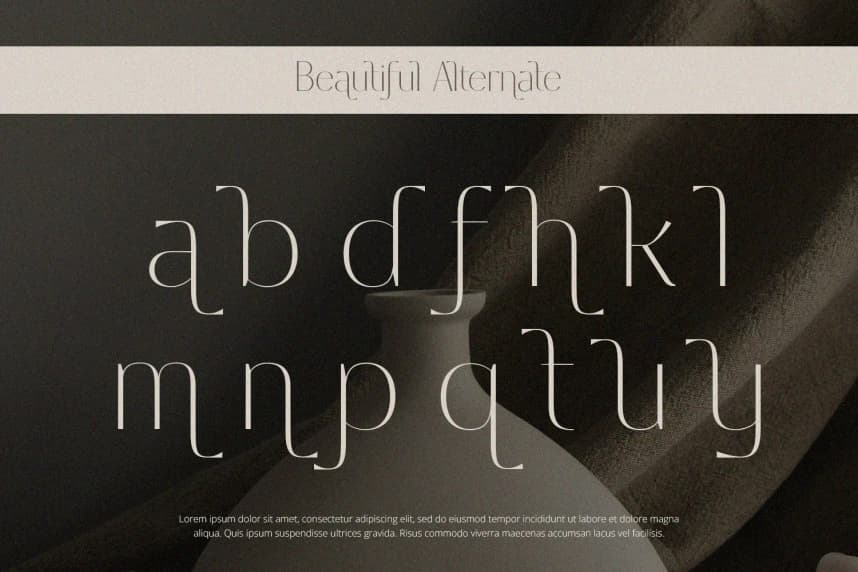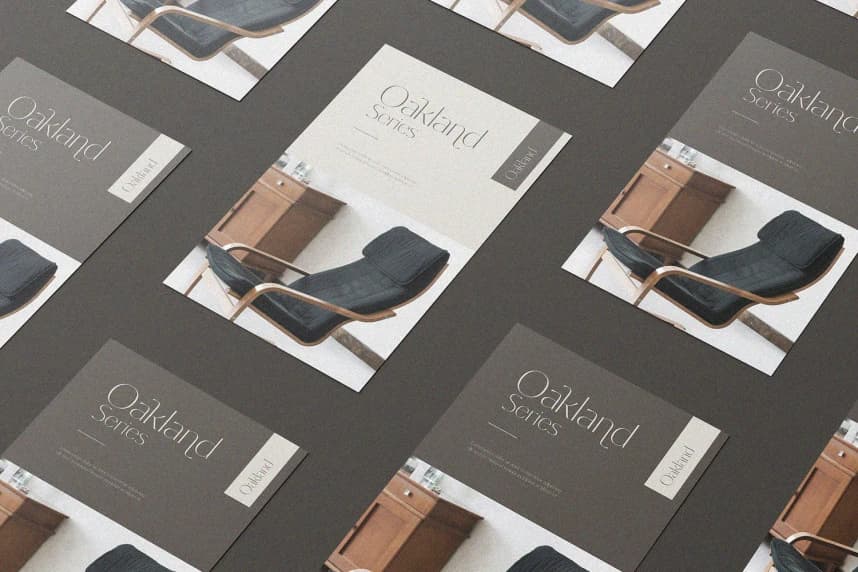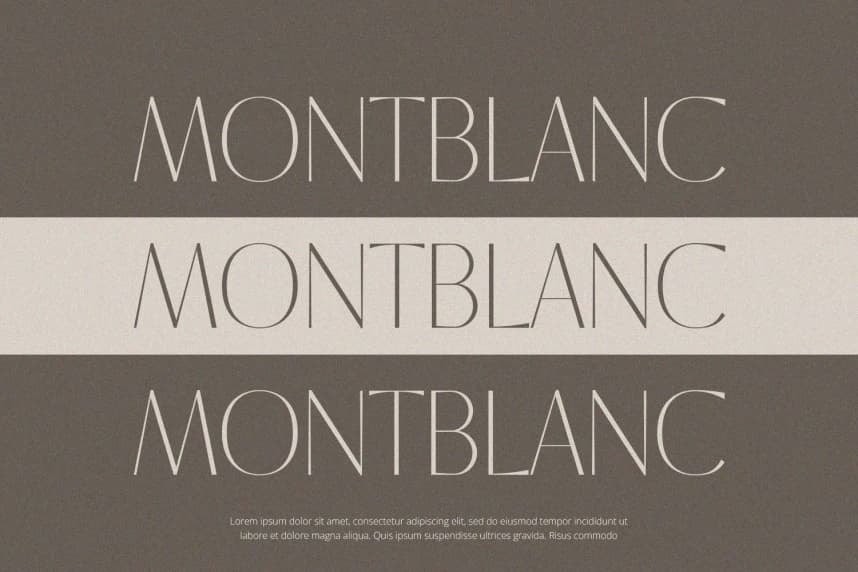
Castelloria - Serif Font, modern bir hissiyat veren bir serif yazı tipidir. Branding, Logo Design, Lettering, Logotype, Clothing, Poster, magazine, packaging, posters, shopping bags, t-shirts, book covers, photography, special events ve diğer design projeleri için mükemmel şekilde kullanılacaktır.
Castelloria - Serif Font, modern hissiyat veren bir serif yazı tipidir. Markalaştırma (Branding), Logo Tasarımı, Lettering, Logotype, Giyim, Poster, dergi, ambalaj, posterler, alışveriş çantaları, tişörtler, kitap kapakları, fotoğrafçılık, özel etkinlikler ve diğer tasarım projeleri için mükemmel bir şekilde kullanılacaktır.